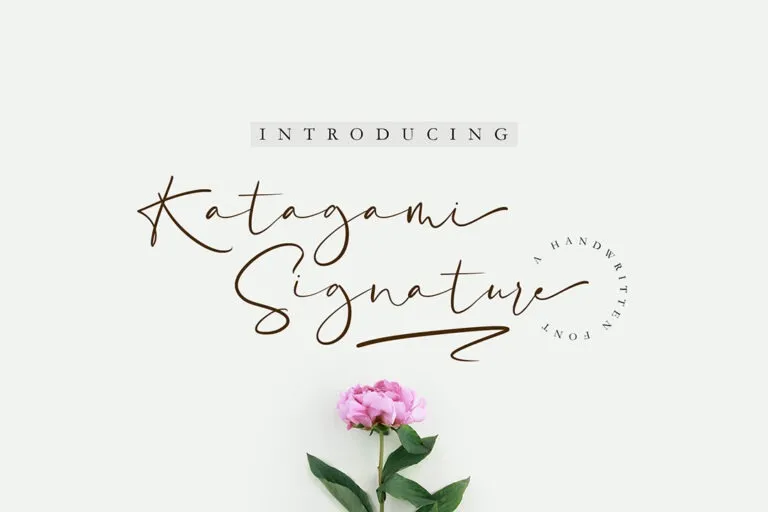
Katagami Font – Download Grátis
Katagami é uma elegante e delicada tipografia script feita para aqueles que adoram a mão-dura do design gráfico. Essa fonte tem uma aparência sofisticada, com curvas únicas e um fluxo de tinta elegante. Criada pelo designer motiontailstudio em 99designs, esta font é perfeita tanto para letras como para selos e embalagens de papel. Suas dobras delicadas e suas formas suaves fazem dela a escolha ideal para qualquer projeto criativo que valorize uma mão-de-obra meticulosa. Katagami tem um original visual que encantará designers, gráficos e amantes da estilização manual, se você está buscando adicionar um toque único a seu próximo trabalho gráfico.